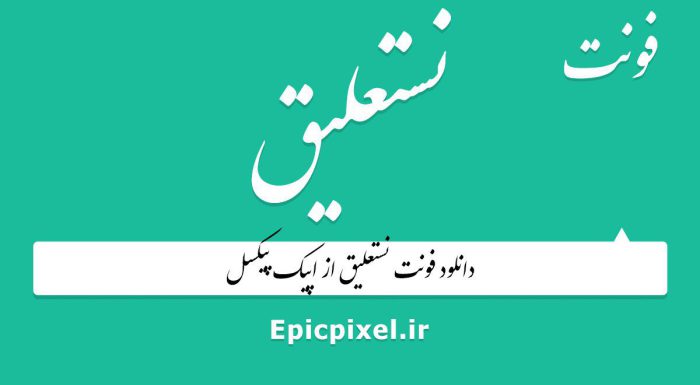
مجموعه کامل فونت های نستعلیق فارسی (۵۶+ فونت)
دانلود مجموعه کامل فونت های نستعلیق (Nastaliq) ، یک آرشیو بسیار جامع برای طراحان و علاقه مندان به خوشنویسی است که شامل 56+ فونت نستعلیق و خوشنویسی دیگر، به عنوان یکی از کاملترین فونت های نستعلیق داخل اینترنت شناخته می شود. نستعلیق، عروس خطوط اسلامی و یکی از زیباترین خطوط نگارشی ایران است که توسط اساتید ایرانی به صورت فونت توسعه یافته. این مجموعه فونت به صورت جداگانه رایگان برای دانلود در فرمت TTF و OTF موجود بوده ولی این آرشیو بصورت کامل شامل هزینه میباشد، قابل استفاده در تمامی نرم افزارهایی که یونیکد را پشتیبانی میکنند (ویندوز، موبایل) و برای انواع طراحی گرافیک و چاپ مناسب است، اگرچه سازگاری آن با نرم افزارهای مختلف ممکن است متفاوت باشد. نستعلیق، عروس خطوط اسلامی و یکی از زیباترین خطوط نگارشی ایران است که ریشه عمیقی در فرهنگ ما دارد.
دانلودمجموعه کامل فونت های نستعلیق: عروس خطوط اسلامی در آرشیوی بی نظیر
مجموعه کامل فونت های نستعلیق (Nastaliq)، یک پکیج کامل و بی نظیر برای طراحان و علاقه مندان به خط نستعلیق و سایر شیوه های خوشنویسی است که امکان استفاده از زیبایی های این خطوط را در محیط های دیجیتال فراهم می کند. این آرشیو شامل 56+ فونت نستعلیق و خوشنویسی دیگر می باشد و به عنوان یکی از کاملترین فونت های نستعلیق داخل اینترنت شناخته می شود. گستره این مجموعه تنها به نستعلیق محدود نمی شود و طبق اطلاعات موجود، شامل ۳۱ فونت ثلث نیز می باشد که نشان دهنده پوشش سبک های مرتبط خوشنویسی در این آرشیو گسترده است.
نستعلیق یکی از شیوه های نگارش خط است که ریشه عمیقی در فرهنگ ایران دارد و در این سرزمین شکل گرفت و بیشتر هم در آن رواج دارد. آن را یکی از زیبا ترین نگاشته های دست بشر و نشانه ای بارز از طبع و سلیقه زیبایی شناختی ایرانیان می دانند. بدون شک زیباترین و ظریف ترین خط در میان خطوط اسلامی است تا جایی که به حق به آن لقب «عروس خطوط اسلامی» داده اند. این خط از ترکیب و تکامل خطوط نسخ و تعلیق حاصل شده است و دارای پیچیدگی ها و زیبایی های خاص خود است.
با گسترش طراحی گرافیک و نیاز به استفاده از خط نستعلیق در محیط دیجیتال، فونت نستعلیق نیز توسط اساتید گرافیک ایران طراحی و ساخته شد. شورای عالی اطلاع رسانی کشور نیز با سرمایه گذاری در این زمینه و در قالب طرح تسما، نقش مهمی در توسعه فونت نستعلیق یونیکد و تقویت حضور خط فارسی در عرصه بین المللی و نگارش رایانه ای و به پاس داشت فرهنگ غنی ایران اسلامی ایفا کرد. پیاده سازی و تولید فونت نستعلیق در محیط های عمومی تولید متن با چالش های متعددی روبرو بود، از جمله تنوع ارتفاع قرارگیری حروف از خط مبنا یا خط کرسی نوشتاری و تنوع بی شمار ترکیب های ممکن حروف در خط نستعلیق. در این راه، رایانه به عنوان یک ابزار کمک کننده عمل کرد و بخش اعظم کار ساخت ترکیب های هنری و رفع مشکلات را کارشناسان خط نستعلیق بر عهده داشتند.
دانلوداین مجموعه شامل فونت های مهم و شناخته شده ای در سبک نستعلیق و مرتبط با آن است. اولین فونت استاندارد یونیکد بنام ” ایران نستعلیق 1″ با سرمایه گذاری شورای عالی اطلاع رسانی و طراحی حسین زاهدی در این زمینه عرضه شد و نسخه های بعدی آن، از جمله ایران نستعلیق 2 (منتشر شده در سال ۱۳۹۱) و ایران نستعلیق 3 (جدیدترین نگارش، بهمن ۱۴۰۰، نگارش 3.03) نیز توسعه یافتند. نسخه سوم شامل صدها تغییر و اصلاح در شکل و اندازه هندسی حروف (طبق اصول خوشنویسی)، اصلاح جایگذاری نقاط و اعراب، و سازگاری بیشتر با اکثر برنامه های گرافیکی روزآمد است. نسخه دوم نیز ویژگی هایی مانند ایجاد کشیدگی و تغییر فرم حروف را در فایل راهنما توضیح می داد. این مجموعه شامل نسخه های مختلفی از ایران نستعلیق است، از جمله: ایران نستعلیق ۱.۰، ۲.۰، ۲.۱، ۳.۰.۳، ان ۱، ان ۲، وب، بی لقمان ۱.۱ ادیت و غیره.
سبک نستعلیق شکسته (Shekasteh) نیز با نسخه های مختلف مانند نسخه بتا و نسخه دیما (که در چند نسخه ارائه شده) در این مجموعه یافت می شود. این فونت ها با حروف شکسته متفاوت وزیبا، امکان تایپ مستقیم خط شکسته را فراهم می کنند و بدون نیاز به ابزار ها و برنامه های خوشنویسی سنتی، می توان از آن ها برای خلق آثاری با این سبک بهره برد.
فونتهای شناخته شده دیگری مانند علوی نستعلیق (Alvi Nastaliq)، میرعماد (Miremad) (که دارنده عنوان بهترین ابزار توسعه خط فارسی در محیط دیجیتال است)، مهر نستعلیق وب (Mehr Nastaliq Web) (توسعه یافته برای نیازهای وب و پشتیبانی انگلیسی)، و دیما نستعلیق تحریری (Dima Nastaliq Tahriri) نیز جزئی از این آرشیو نستعلیق هستند. این مجموعه بیش از ۵۶ فونت مختلف در سبک نستعلیق و نستعلیق شکسته را در بر میگیرد.
کاربردهای مجموعه فونت های نستعلیق در طراحی گرافیک و وب
با توجه به زیبایی بی نظیر، اصالت فرهنگی، و قابلیت های متنوع ارائه شده در این مجموعه فونت نستعلیق، کاربردهای آن در دنیای طراحی گرافیک و وب بسیار گسترده است. این قلم ها یکی از پرکاربرد ترین و شناخته ترین فونت های مورد استفاده در دنیای گرافیک و طراحی هستند. از آن ها می توان به منظور خوشنویسی دیجیتال، تایپ در نرم افزارهای ورد ، آفیس ، فتوشاپ ، کورل، ساخت عکس نوشته های گرافیکی و … استفاده کرد. همچنین مناسب برای انواع طراحی، طراحی انواع پوستر، ایجاد طرح های تایپوگرافی (چیدمان حروف) و غیره می باشند. در مجله ها، پشت جلد کتاب ها، سرلوحه ها، طرح تمبر، بزرگداشت ها نیز به کار می روند. فونت نستعلیق برای استفاده در وب و موبایل (اندروید، iOS) و در اینستاگرام و رسانه های دیگر نیز مناسب است. قابلیت هایی نظیر کشیدگی، تغییر فرم حروف و تایپ مستقیم (در برخی نسخه ها) انعطاف پذیری بالایی در خلق آثار هنری و تجاری فراهم می کند و امکان نمایش زیبایی نستعلیق در پلتفرم های مختلف را می دهد.